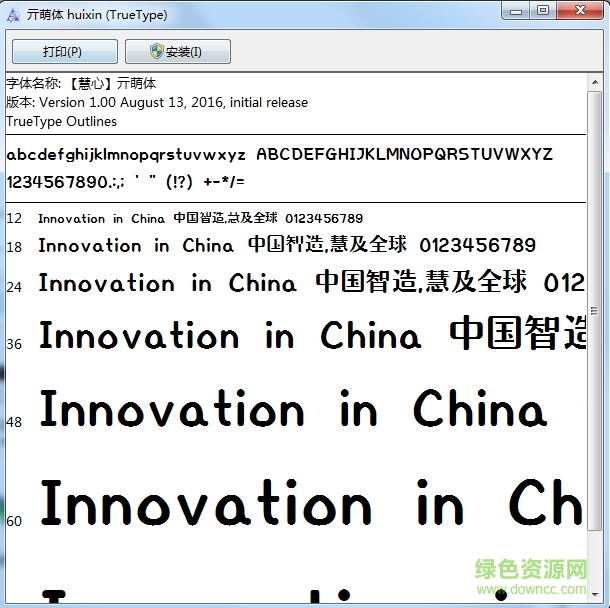
軟件介紹 軟件標簽: 慧心 字體 亓萌體是慧心字體中一款很簡單可愛的書法字體,擁有多種書法的聚合風(fēng)格,但又顯得獨特而有韻味,綠色資源網(wǎng)為大家?guī)磉@款字體的TTF版,歡迎下載體驗喲!亓萌體字體介紹亓(qi)萌體是一款自己秀麗,擁有幼圓和楷書字體風(fēng)格的慧心字體,獨特的風(fēng)格讓它在排版設(shè)計、廣告創(chuàng)意、名片印刷等行業(yè)深受大家喜歡!亓萌字體安裝方法一:控制面板/字體/文件/安裝新字體;方法二:直接將字體復(fù)制到C:\WINDOWS\Fonts。方法三:針對win7系統(tǒng),用戶只需選中字體右鍵安裝即可。 軟件截圖 上一張下一張(1 / 1) 安裝詳細截圖 其他版本下載 標題 大小 更新日期 下載 下載地址 電腦版 慧心亓萌字體 點擊報錯 軟件無法下載或下載后無法使用,請點擊報錯,謝謝! 關(guān)閉報錯反饋 請描述您所遇到的錯誤,我們將盡快予以修正,謝謝! *必填項,請輸入內(nèi)容 本類最新 dreamweaver字體庫 首爾南山體字體 v1.06 官方版 潮字社風(fēng)云簡ttf 潮字社凌渡鯤鵬簡體字體 潮字社曾玉波手書簡字體 微博慧心字體 相關(guān)文章 Photoshop字體安裝使用方法和技巧 如何解決“無法新增字體”問題 Win 7系統(tǒng)安裝字體方法 網(wǎng)頁字體大小設(shè)置方法 怎么改網(wǎng)頁字體大小 在Linux系統(tǒng)中安裝字體的幾種方法 windows7字體顯示問題:打開某些程序的時候顯示的是亂碼 用戶評論 熱門評論 最新評論 發(fā)表評論 查看所有評論(0) 昵稱: 請不要評論無意義或臟話,我們所有評論會有人工審核. 字數(shù): 0/500 (您的評論需要經(jīng)過審核才能顯示)